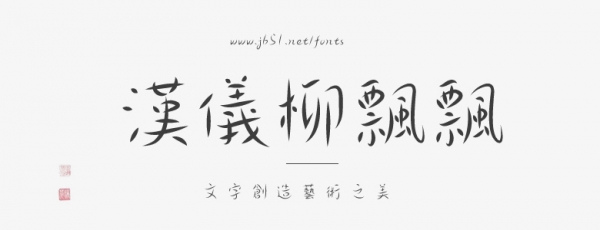
漢儀柳飄飄簡(jiǎn)繁字體字形剛?cè)嵯酀?jì),流暢自然,書(shū)寫(xiě)姿勢(shì)獨(dú)特,既具有美感,又不失可讀性。其設(shè)計(jì)細(xì)膩,線條流暢、輕盈,整個(gè)字體通透明亮,為文學(xué)、書(shū)法、印刷、包裝設(shè)計(jì)等領(lǐng)域提供了較好的視覺(jué)效果